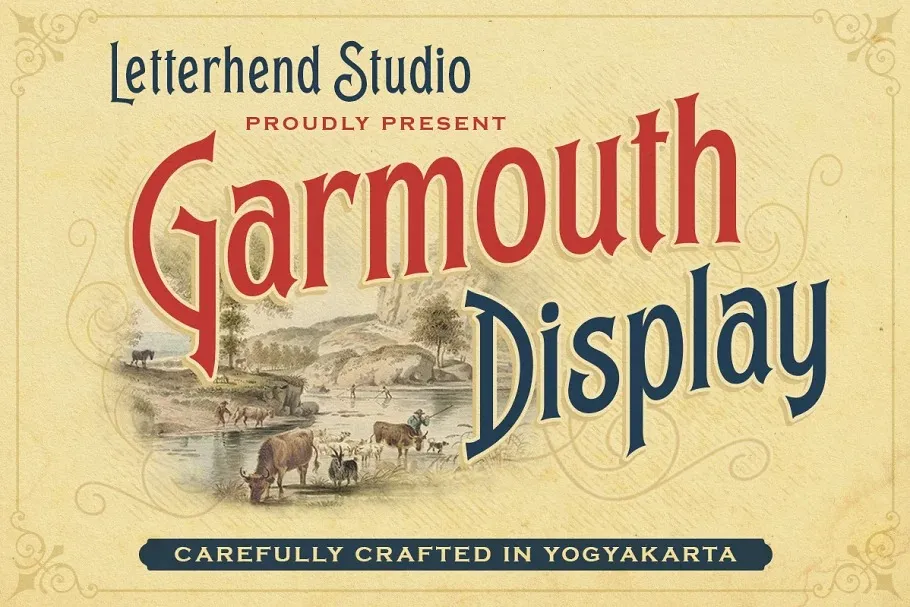
A fonte Garmouth Font é uma seleção única para arquitetura visual moderna e vintage. Desenhada com mão e inspirada em estandartes clássicos dos anos 60 e 70, esta tipografia display traz um encanto sofisticado junto a sua aparência antiquada. Garmouth é perfeitamente adaptável para uso em logotipos, cartões de convite ou etiquetas formais, desde revistas até livros de novelas, passando por carteiras e embalagens. Suas serifas únicas combinam elegância com uma atmosfera nostálgica do início do século XX, tornando-a perfeita para qualquer aplicação de publicidade. Ideal tanto para a criação de marcas distintos quanto para texturas formais em diversas mídias gráficas.